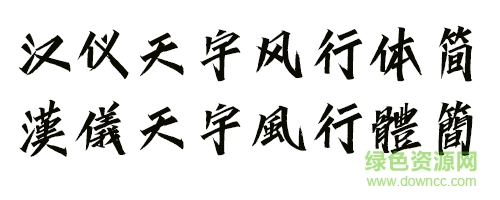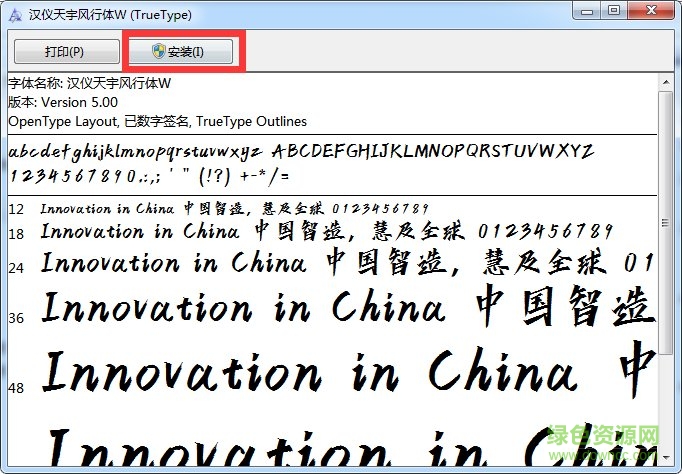
漢儀天宇風行體
漢儀天宇風行體包含了簡體和繁體字體文件。這兩款字體都可以用于設計行業(yè)。字體蒼勁有力,很鋼筆字體外形很相似。需要這款字體的朋友趕快來綠色資源網(wǎng)下載吧。
漢儀天宇風行字體線條粗壯有力,具有靈活的適用性,創(chuàng)意特點鮮明,應用性明顯,能夠應用于文本裝潢、信息展示、網(wǎng)頁設計、篆刻制模、數(shù)據(jù)制作等場景!歡迎用戶前來綠色資源網(wǎng)下載使用。
漢儀天宇風行字體輸出的文字看起來很飄逸,對這類字體一直都很著迷。
非常喜歡這個字體,用來排版設計效果很好!